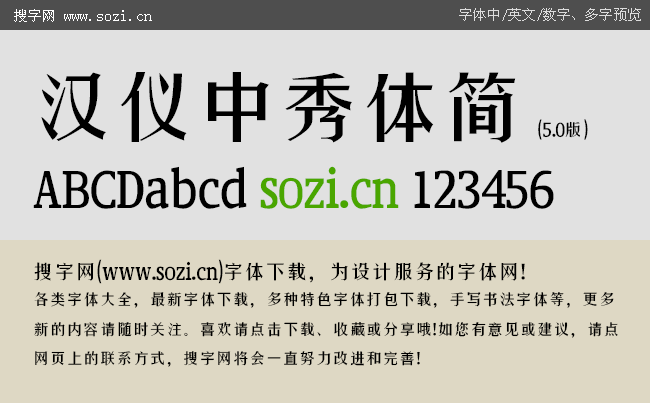
漢儀中秀體簡5.0版
搜字網(wǎng)給大家提供一款漢儀中秀體簡5.0版中文字體下載。漢儀中秀體字形結(jié)構(gòu)穩(wěn)定,配合設(shè)計簡潔的筆畫,排版時整體線性效果更加突出,使閱讀更加流暢。 筆畫風(fēng)格上融合了黑體與宋體的特征,線條簡潔,氣質(zhì)圓柔、秀美,風(fēng)格靈動、時尚。筆畫間的相互呼應(yīng)更使得字體整體結(jié)構(gòu)統(tǒng)一完整、避免了結(jié)構(gòu)的呆板、生硬。可應(yīng)用于平面設(shè)計、出版印刷、廣告設(shè)計、包裝設(shè)計等領(lǐng)域。